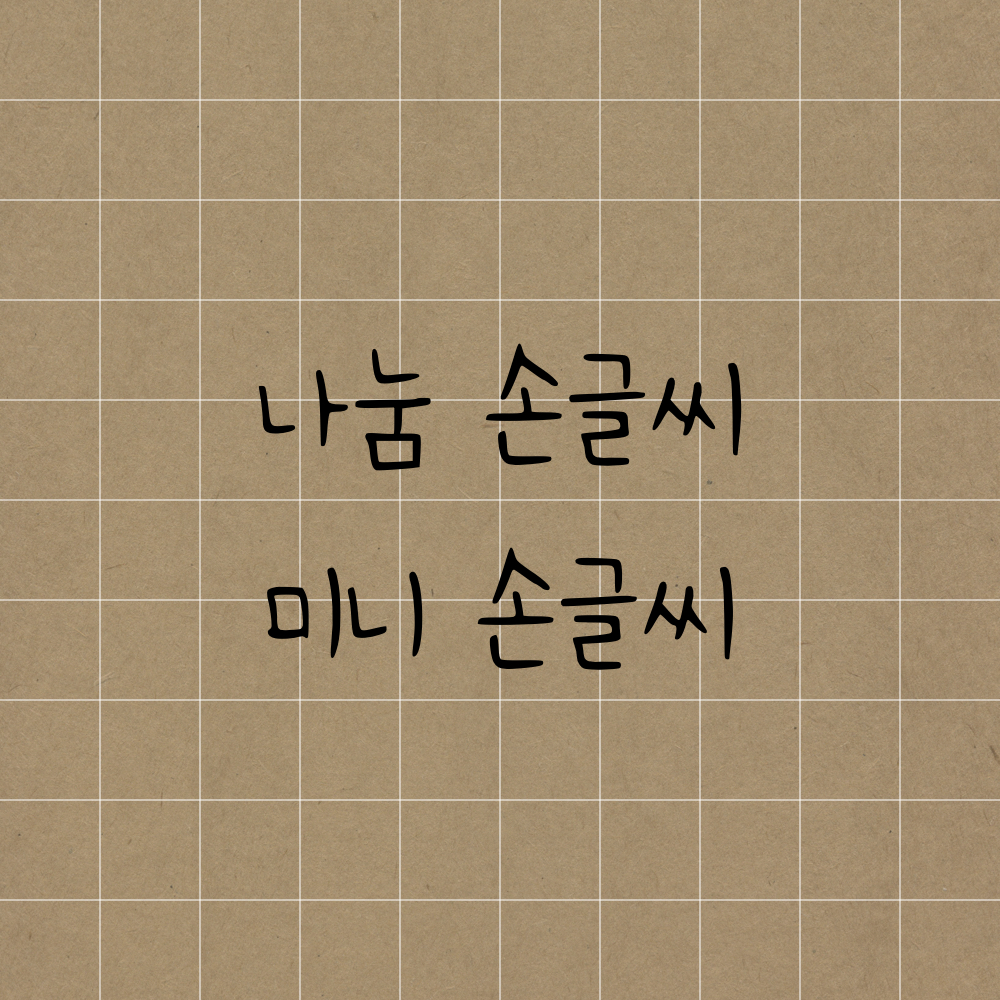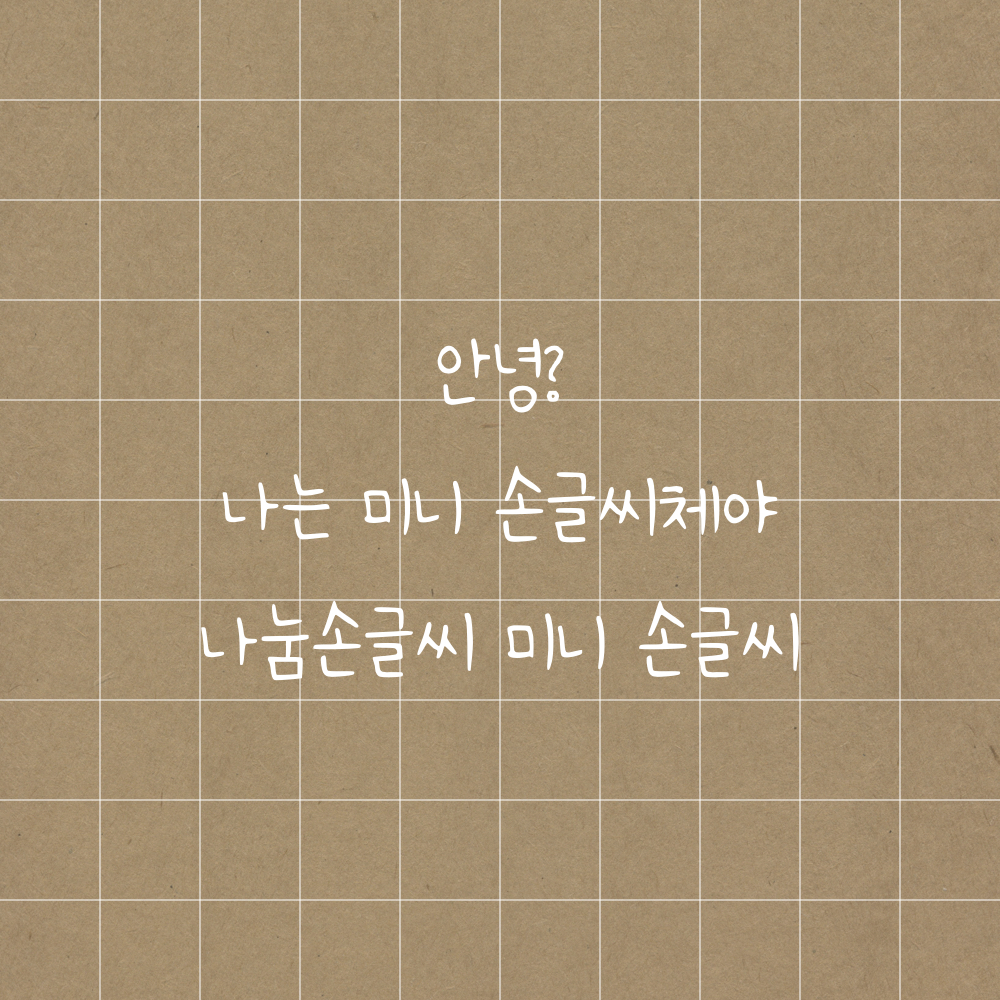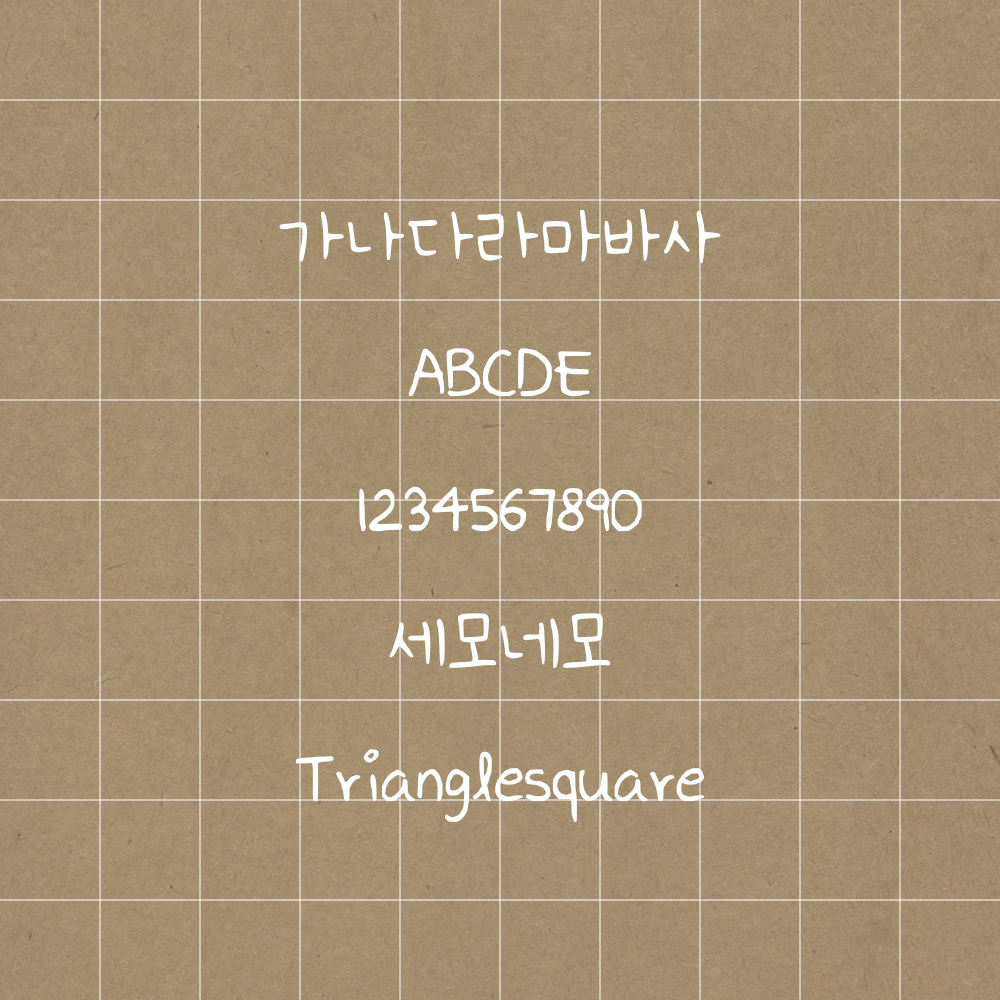
오늘의 폰트는 미니 손글씨체입니다🫶
영어 글씨체가 매력적인 폰트를 가지고 왔습니다🤓
아이패드로 손필기를 할 때 글씨체가 마음에 들지 않는다면 마음이 싹 사라지기 마련이죠.
그래서 저는 손글씨 폰트로 텍스트 필기를 하고 있습니다. 오늘은 제가 자주 애용하는 폰트를 소개하겠습니다😆
종이 필기체와 아이패드 필기체가 달라 아쉬웠는데 저의 종이 필기체와 가장 비슷해서 바로 다운로드했습니다💜
영어 폰트는 제 필기체와 조금 다르지만 꽤괜이더라고요☺️
꽤괜 정도가 아니라 영어를 더 자주 사용하는 것 같기도~?💛🤓